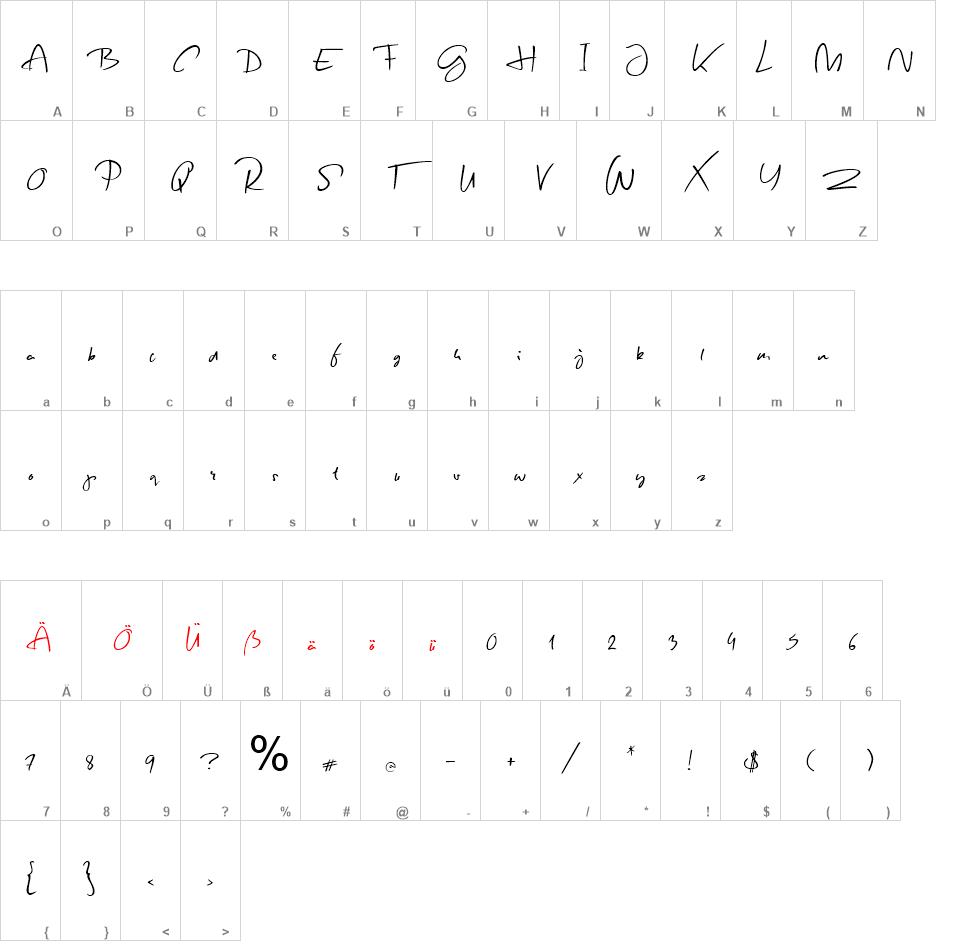
Spring Script
FRÜHLINGS-SCHRIFT ist eine zufällige handgeschriebene Schriftart.
Es sieht etwas unordentlich aus und einige Wörter funktionieren möglicherweise nicht gut, aber einige sehen perfekt für das Logo aus. Gleiches gilt besonders für alle Caps. Versuche es ;)